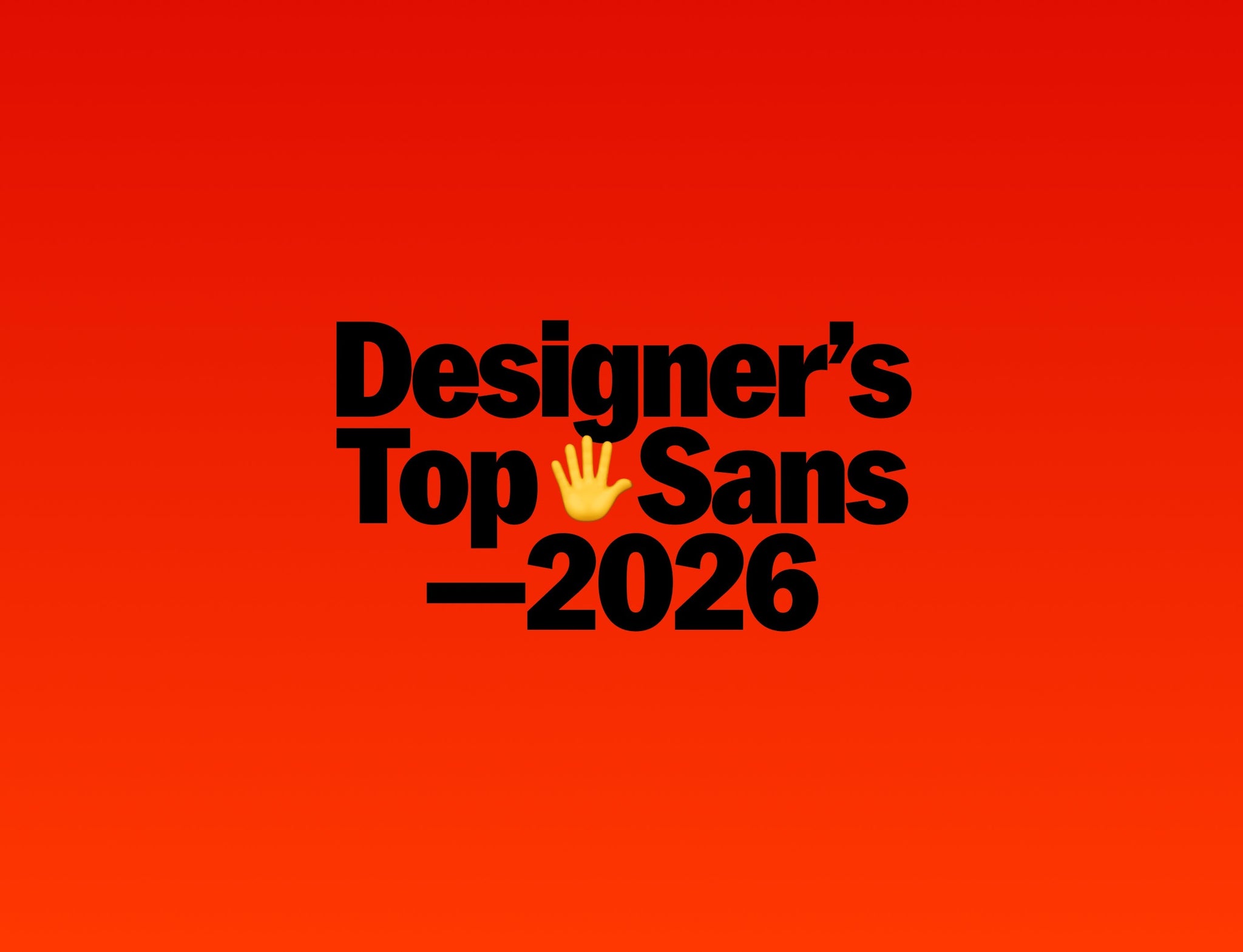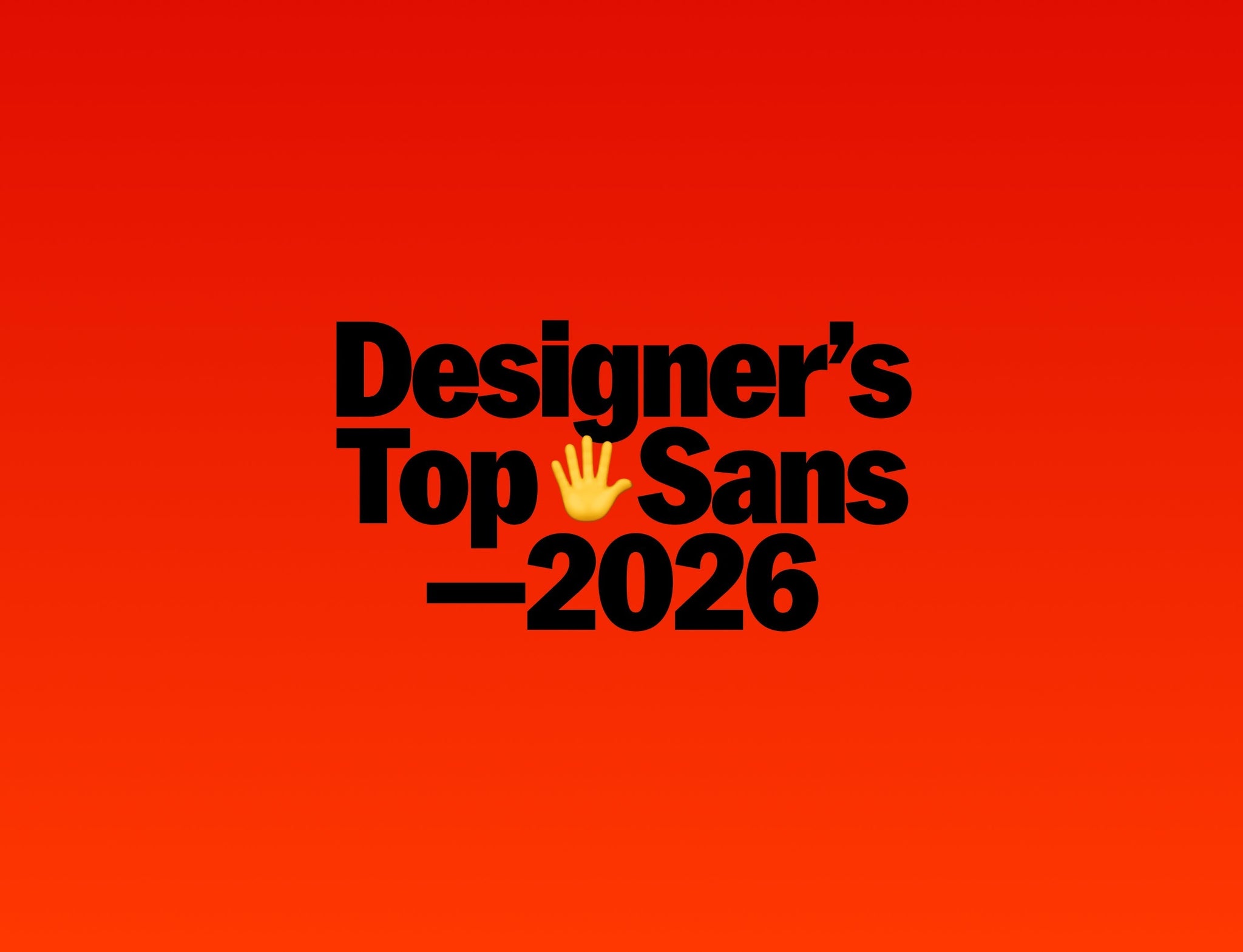
Chez Pangram Foundry, plusieurs familles de polices sans-serif sont devenues des incontournables pour les designers grâce à leur polyvalence, leurs fortes personnalités et leur fabrication exceptionnelle.
Voici, d'après ce que nous pouvons en tirer, cinq des polices sans-serif les plus populaires de la fonderie et les raisons pour lesquelles des créatifs comme vous y reviennent sans cesse.
Neue Montreal
Neue Montreal est devenue l'une des polices les plus reconnaissables de Pangram Pangram. Inspirée par le riche héritage du design montréalais, elle combine la neutralité d'une grotesk classique avec de subtils détails contemporains. Sa polyvalence la rend également efficace dans le branding, les sites web, les systèmes éditoriaux et les interfaces utilisateur, ce qui en fait un choix fiable pour les designers à la recherche d'une police de caractère moderne et polyvalente avec de la personnalité.
Neue York
Neue York réunit la sophistication de la typographie éditoriale et la simplicité d'une police sans-serif contemporaine. Ses proportions élégantes et ses détails raffinés créent une voix distinctive qui se veut haut de gamme sans être trop formelle. Les designers utilisent souvent Neue York dans les projets de branding et d'édition où ils souhaitent une typographie moderne, affirmée et élégante.
Museum
Museum est une police sans-serif géométrique qui équilibre la clarté et la chaleur. Sa construction épurée et son caractère accessible la rendent particulièrement efficace pour la conception d'identités, d'emballages et de projets culturels. Museum est contemporaine sans être à la mode, offrant aux designers une police polyvalente qui peut s'adapter à une large gamme de systèmes visuels tout en conservant une forte personnalité.
Mori
Mori a été conçue pour être une famille de polices sans-serif très fonctionnelle et flexible. Avec sa vaste gamme de graisses et de styles, Mori peut prendre en charge tout, du branding minimaliste aux mises en page éditoriales complexes. Les designers apprécient son apparence épurée, son excellente lisibilité et sa capacité à rester visuellement intéressante, même dans les grands systèmes où la cohérence est essentielle.
Räder
Räder se distingue par son caractère industriel distinctif et sa présence affirmée. Inspirée par les formes mécaniques et la précision de l'ingénierie, elle offre une alternative unique aux designs sans-serif plus traditionnels. Les designers choisissent souvent Räder lorsqu'ils veulent qu'un projet soit audacieux, contemporain et mémorable, tout en conservant la fonctionnalité attendue d'une police professionnelle.
La collection sans-serif de Pangram est un succès parce qu'elle combine l'excellence technique et un design distinctif. Plutôt que de s'appuyer sur des solutions génériques, chaque famille apporte sa propre voix et sa personnalité tout en restant pratique pour des projets concrets. Un support linguistique étendu, un espacement réfléchi et des fonctionnalités OpenType modernes garantissent que ces polices sont aussi performantes qu'esthétiques. Que vous construisiez une identité visuelle, conceviez un site web ou créiez un système éditorial, des polices comme Neue Montreal, Neue York, Museum, Mori et Räder démontrent pourquoi Pangram reste un favori parmi les designers du monde entier.